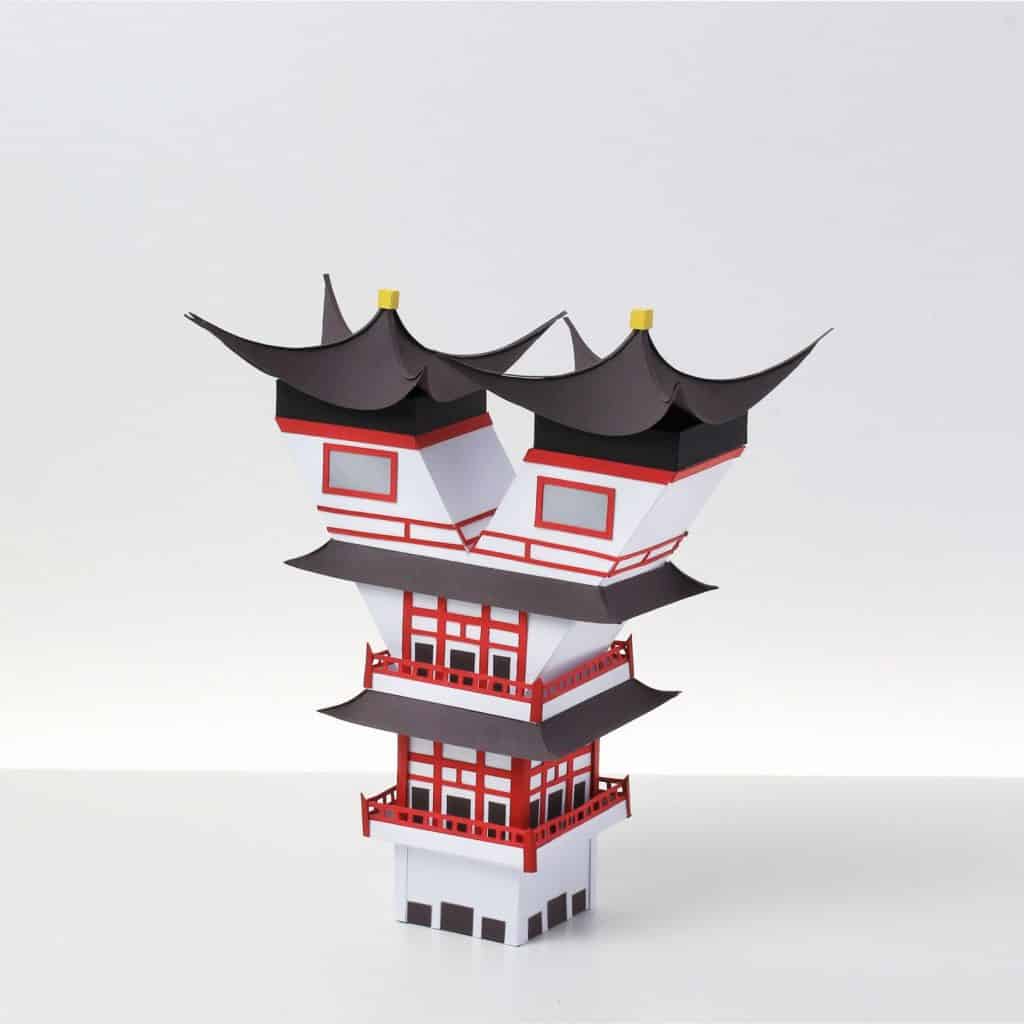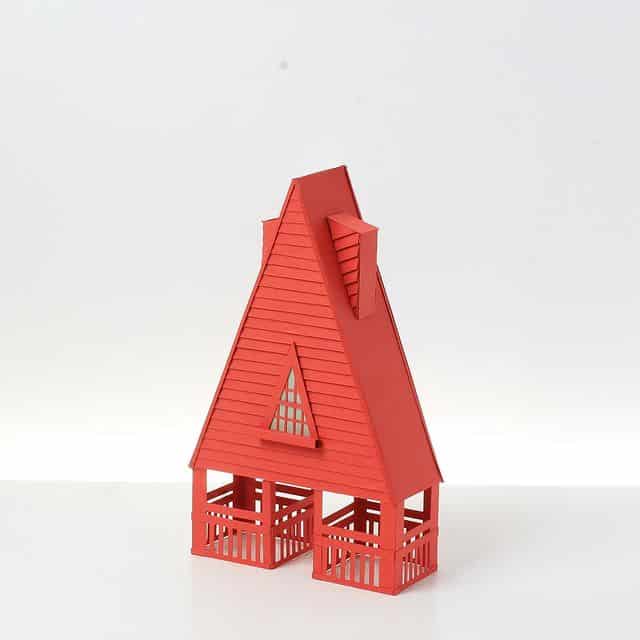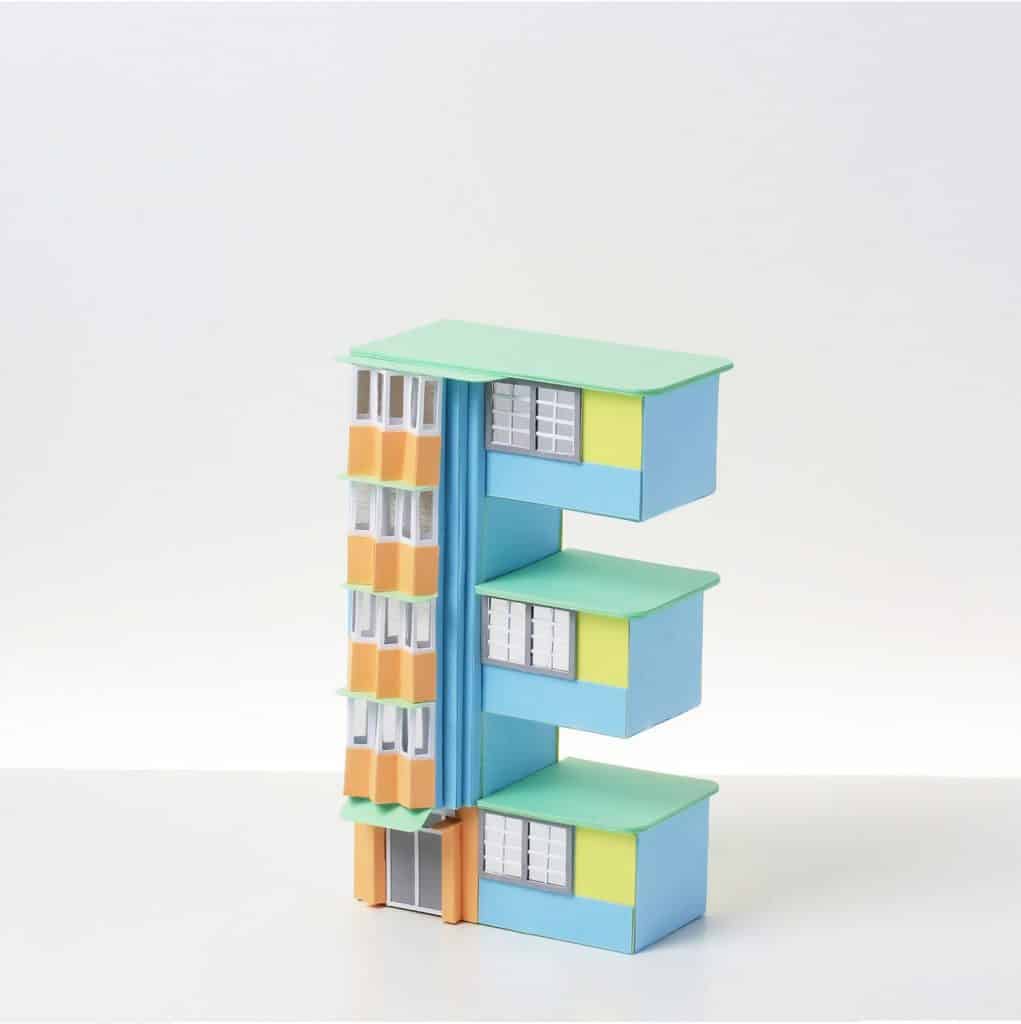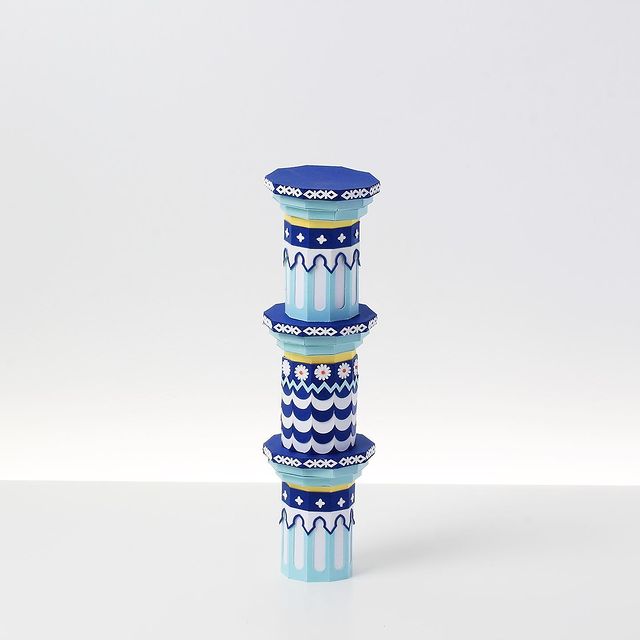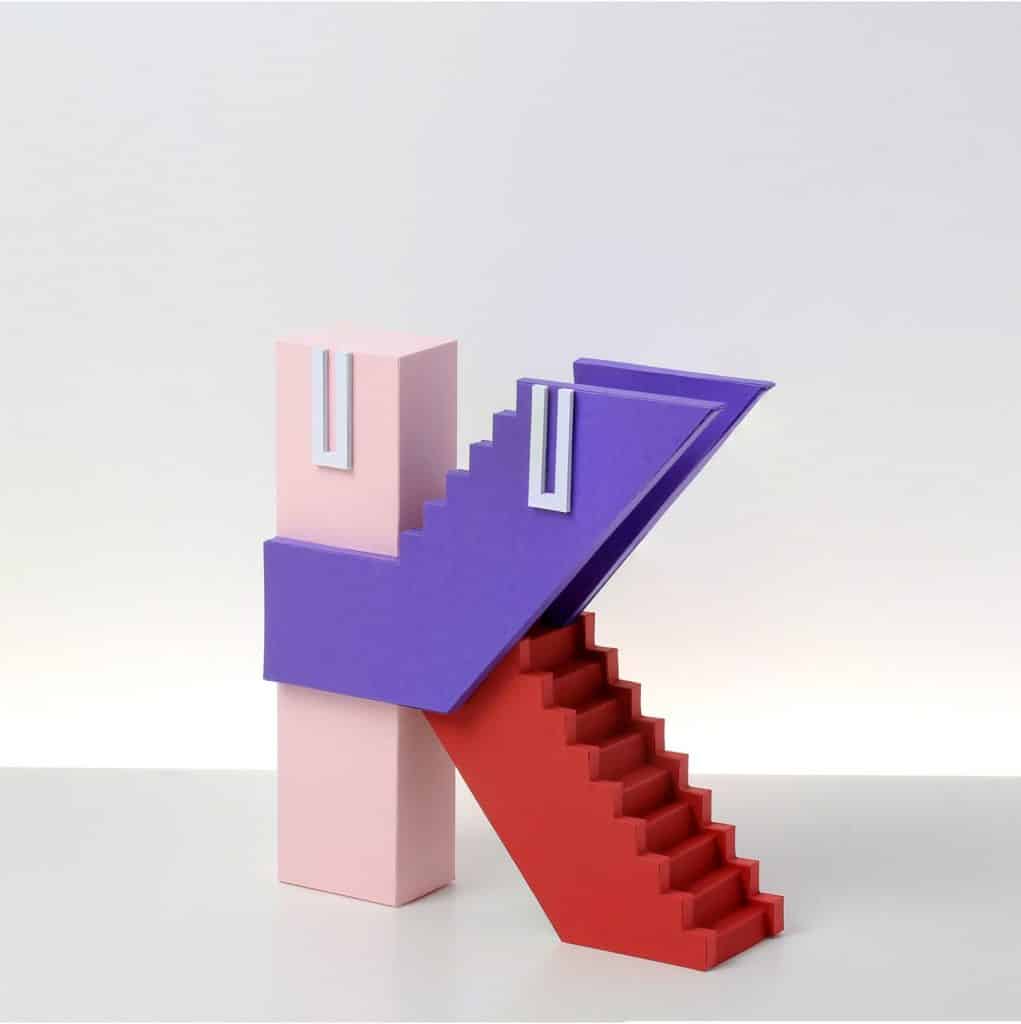
El arte en papel de la diseñadora y creativa Mel Edwards, mezcla su amor por la tipografía, la arquitectura, el arte del papel y la estética de Wes Anderson.
Para la edición de 2021 de 36 Days of Type, Mel decidió crear una serie tipográfica, a través de arte en papel artesanal al mejor estilo de uno de los directores de cine y arte más relevantes de los últimos años; Wes Anderson.
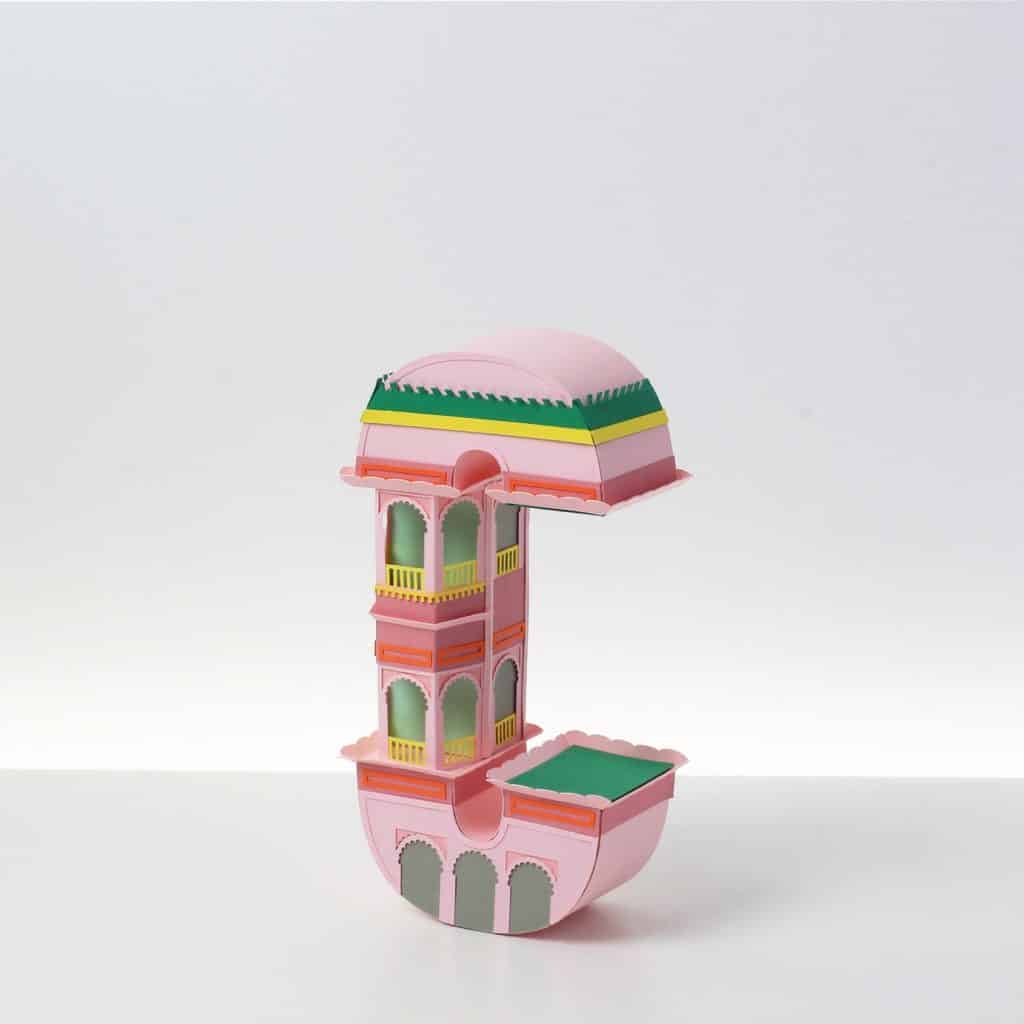
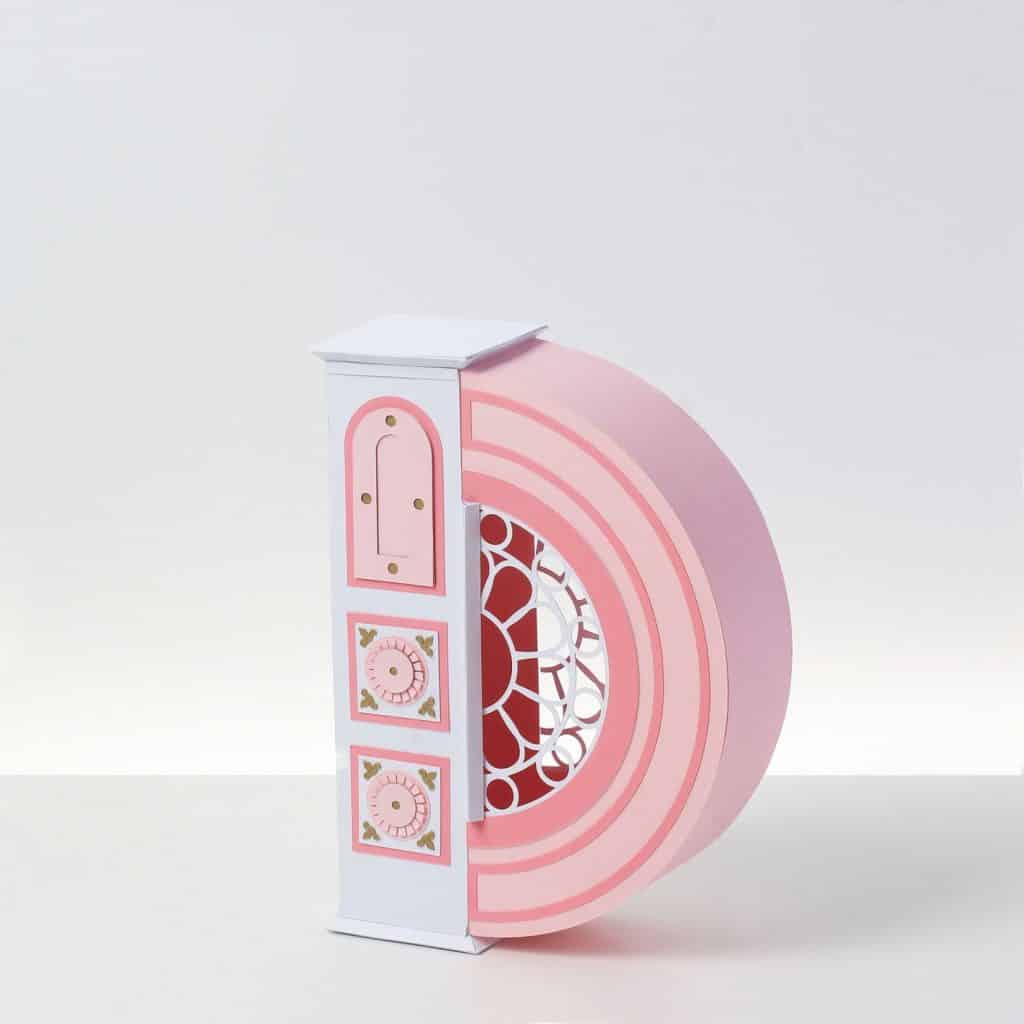
Utilizando colores pastel, la simetría y la estética del director Wes Anderson, Mel crea su brillante serie de letras en papel, lo que le llevó 250 horas de trabajo en total, mas la fotografía y la edición. que, aunque parezca un proceso digital, todo es hecho a mano.